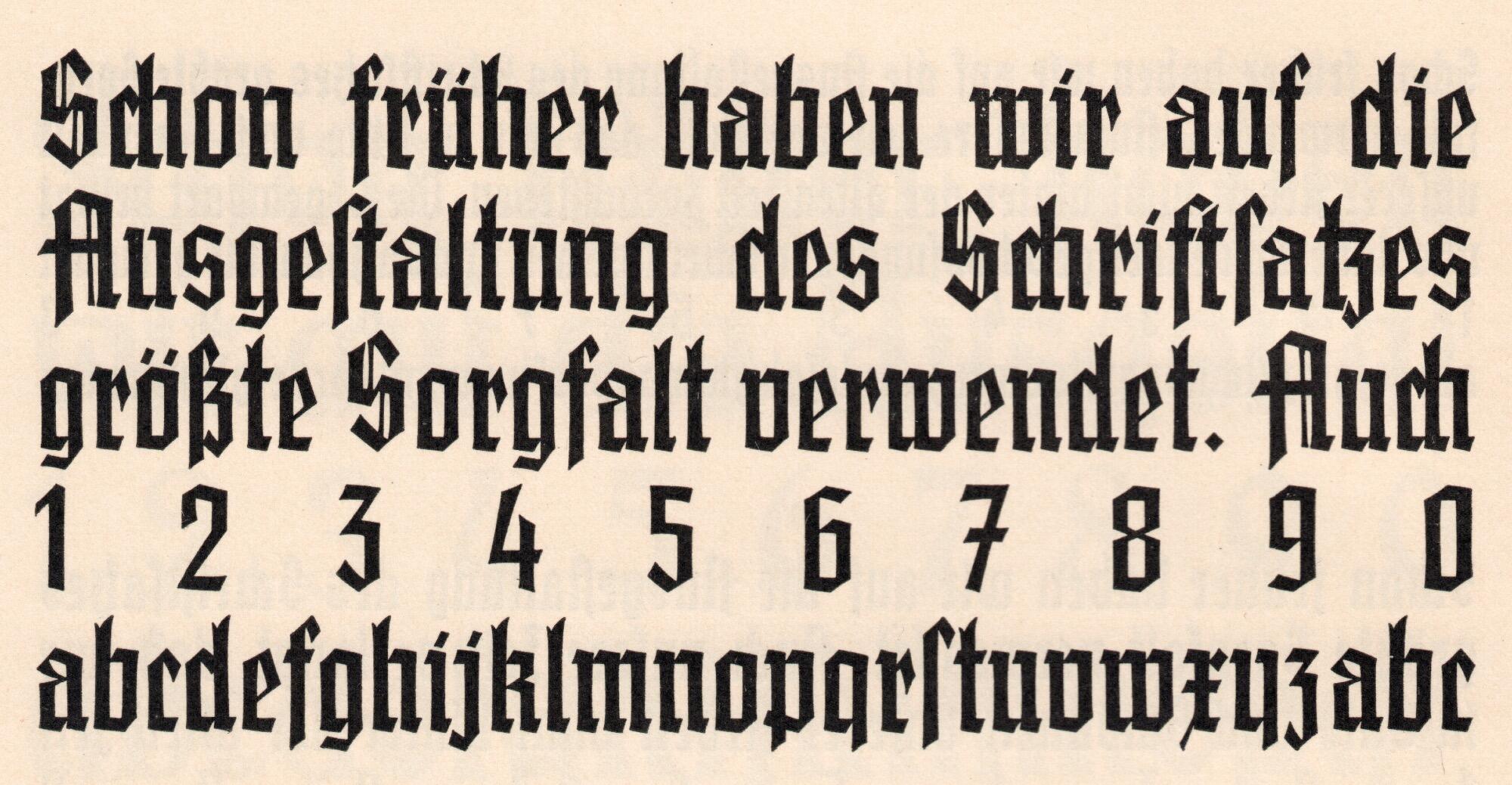
Font-Wiki: Germroth-Schrift
Die Germroth-Schrift (auch Germroth Deutsch) ist eine schlichte Gotisch, benannt nach ihrem Gestalter Georg Germroth. Die Schrift erschien 1935 in einem Schnitt beim Ludwig & Mayer.
Digitalisierungen sind nicht bekannt.